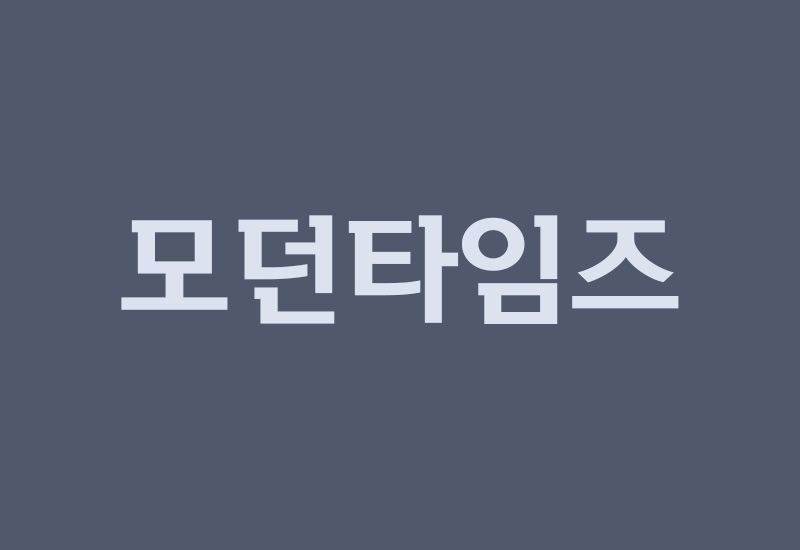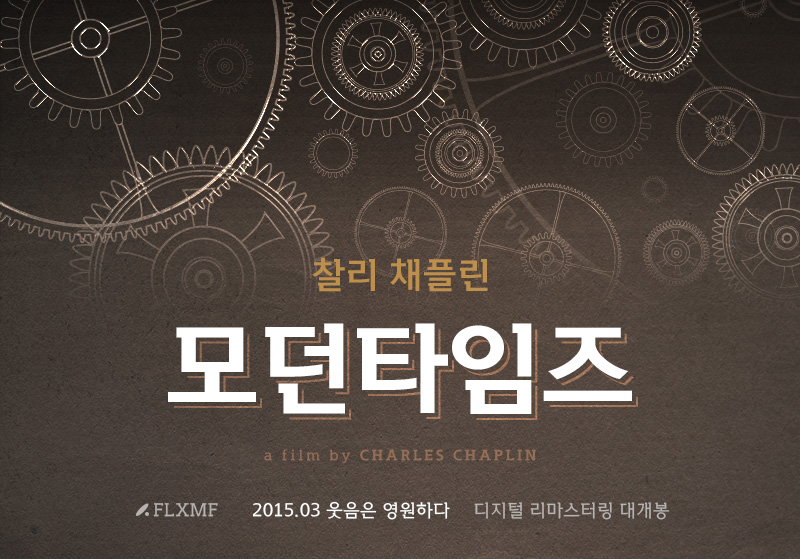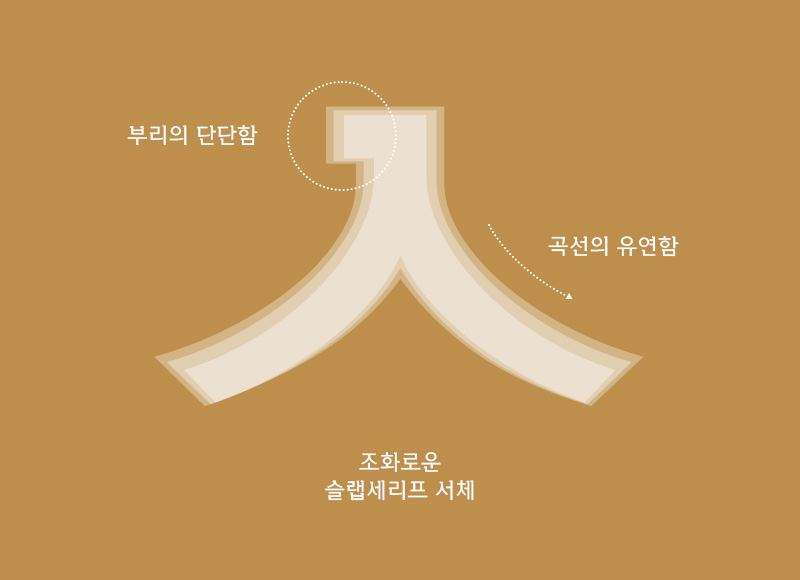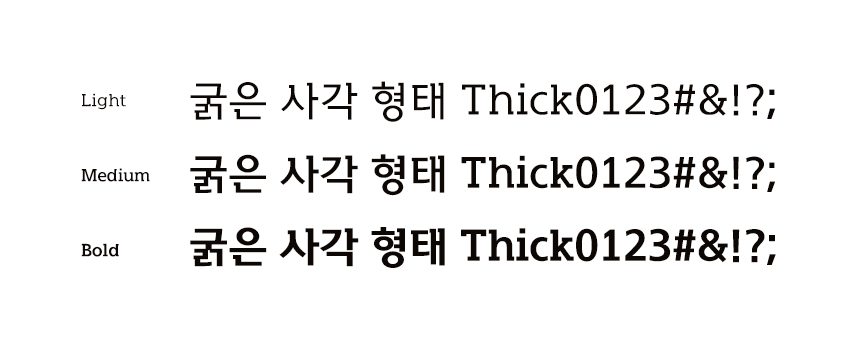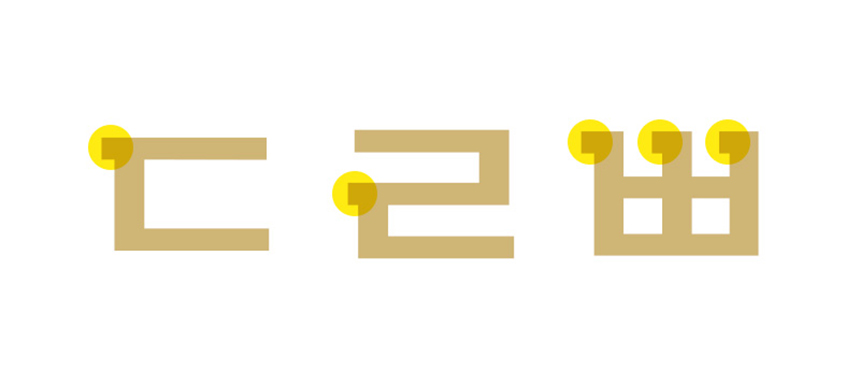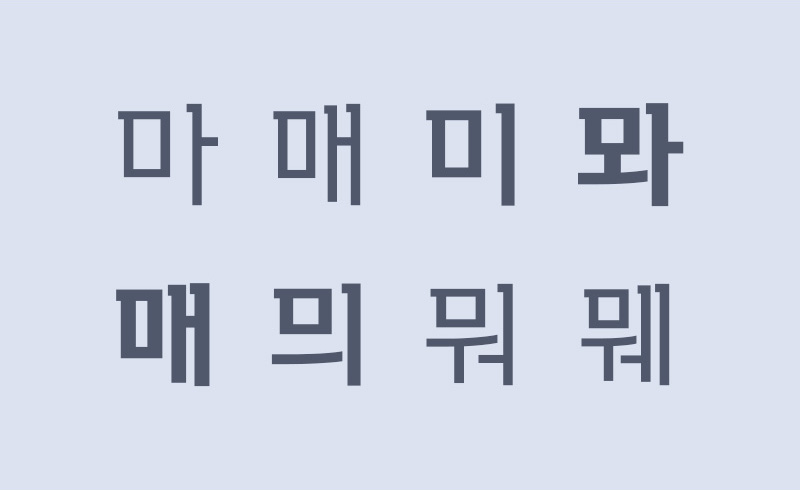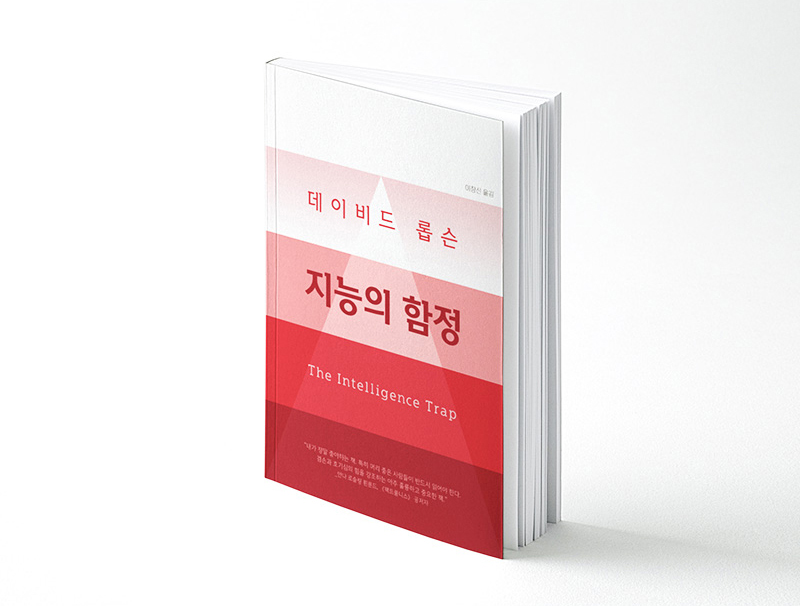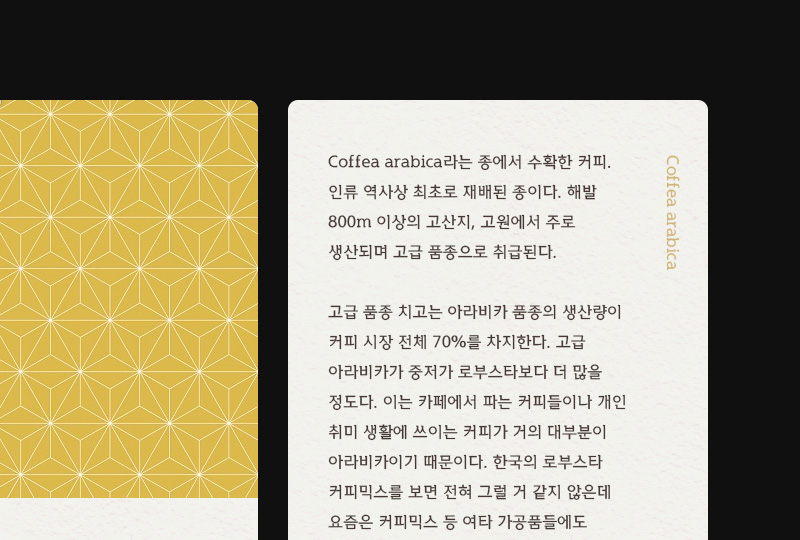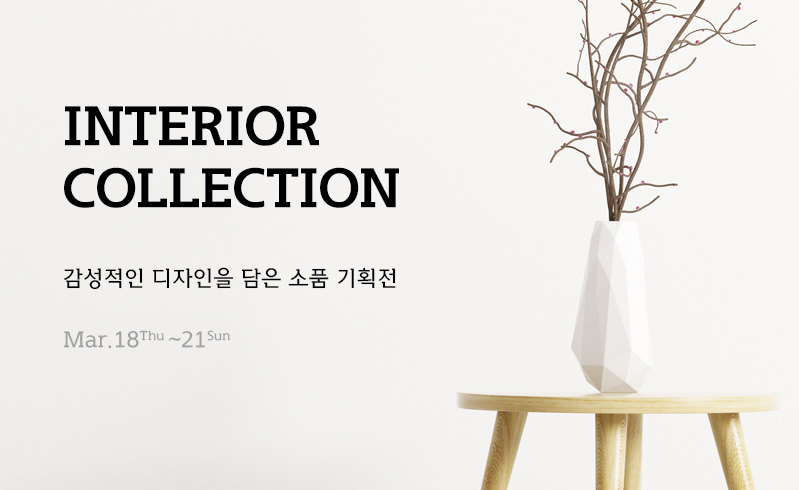
Once upon a time in Modern Times.
오늘 만나볼 6월의 신규 폰트는 과거로 시간 여행을 떠난 듯한 기분을 느끼게 해주는 서체 「Rix모던타임즈」입니다. 서체의 단단하고 굵은 직각 세리프와 유연한 곡선 획의 조화가 영화 '모던 타임즈(Modern Times, 1936)' 속 톱니바퀴를 떠오르게 하는데요. 19세기 최초의 슬랩 세리프 이집션체Egyptian를 모티브로 한 각진 세리프에 현시대의 모던한 디자인을 적용했습니다.
산업혁명과 시대의 산물 🔧🔩
모던타임즈라는 서체명은 19세기 초 산업혁명이 일어났던 기계시대에 대한 이야기를 다룬 영화, 그리고 그 시대에 탄생한 슬랩 세리프 서체가 배경이 되어 탄생했습니다. *슬랩 세리프는 글자와 기호를 이루는 획의 일부 끝이 돌출된 형태를 띠는 세리프 서체의 한 양식으로 세리프가 굵은 사각 형태의 모습을 보이는 서체 스타일입니다.
*슬랩 세리프 Slab Serif
슬랩(Slab)의 사전적 정의는 '두껍고 반듯한 조각'입니다. 이 ‘두꺼운 조각’은 이 서체 양식을 대표하는 무겁고 각이 진 세리프를 가리키는 것이며 이는 산업혁명 시대의 시각적 산물입니다. 19세기에는 기계 생산으로 가능해진 대량 생산과 판매가 진행되면서 광고의 시대가 열렸고, 짧은 시간에 주목을 끌고 강한 시각적 인상을 줄 수 있는 활자체에 대한 요구가 증대하면서 세리프의 굵기와 모양에 있어서 극단적인 표현까지 등장하게 되었습니다.
1820년 로버트 손Robert Thorne이 제목용 슬랩 세리프 활자를 깎아 '이집션'이라 명명했는데요. 활자의 각지고 두꺼운 세리프가 고대 이집트의 건축 유물과 닮아있었기 때문입니다. Rix모던타임즈 서체에서 보이는 형태적인 특징은 많은 부분 이 서체에서 모티브를 얻었습니다. 모던타임즈 서체는 찰리 채플린의 영화 '모던 타임즈'의 배경이기도 했던 산업혁명 시대에 나타난 두꺼운 블록형 세리프를 닮은 현대적인 폰트로 재탄생했습니다.
보다 현대적인 Slab Serif 💻
Rix모던타임즈는 슬랩 세리프 양식의 서체로 볼 수 있지만 기존 스타일의 형태적 특성과 함께 현시대에 어울리는 모던한 디테일들이 조화롭게 적용된 서체입니다. 그 특징들을 살펴볼까요.
먼저 자소에서 단단한 직각의 세리프를 확인할 수 있는데요. 군더더기 없는 깔끔한 사각 형태의 부리에서 유연한 곡선으로 떨어지는 획의 조화가 돋보입니다.
획 두께의 대비 차이가 없이 일정한 굵기로 제작되었고, 기존의 슬랩 세리프들과는 다르게 가변폭을 사용하여 보기에 편안하도록 설계했습니다. 굵기에 따라 Light, Medium, Bold 3가지의 웨이트로 파생했습니다.
획 순서를 고려해 적용한 세리프는, 다소 둔탁해 보일 수 있는 각이 진 형태를 보완하여 쉐입이 보다 자연스러워 보일 수 있도록 디자인했습니다. 직각 세리프가 단단한 힘을 실어 주지만 과하지 않게 디자인되어 전체적으로 단정한 느낌을 줍니다.
이렇게 활용해 보세요🎨📚
사용성을 높인 3종의 웨이트로 획의 두께에 따라 다양한 느낌을 연출할 수 있습니다. 두꺼운 굵기의 Bold를 활용해 북 커버의 타이틀로 사용할 수 있고, Medium이나 Light 굵기로는 텍스트가 많은 리플릿, 포스터 등 각종 인쇄물의 본문으로 사용하기 좋습니다.
폰트를 어떻게 활용하느냐에 따라 차분하고 단정한 분위기부터 모던하고 감각적인 디자인까지 폭넓은 활용도를 갖고 있습니다. 또한 영문과 숫자 스타일도 통일성 있게 제작되어 조화롭게 사용할 수 있습니다.